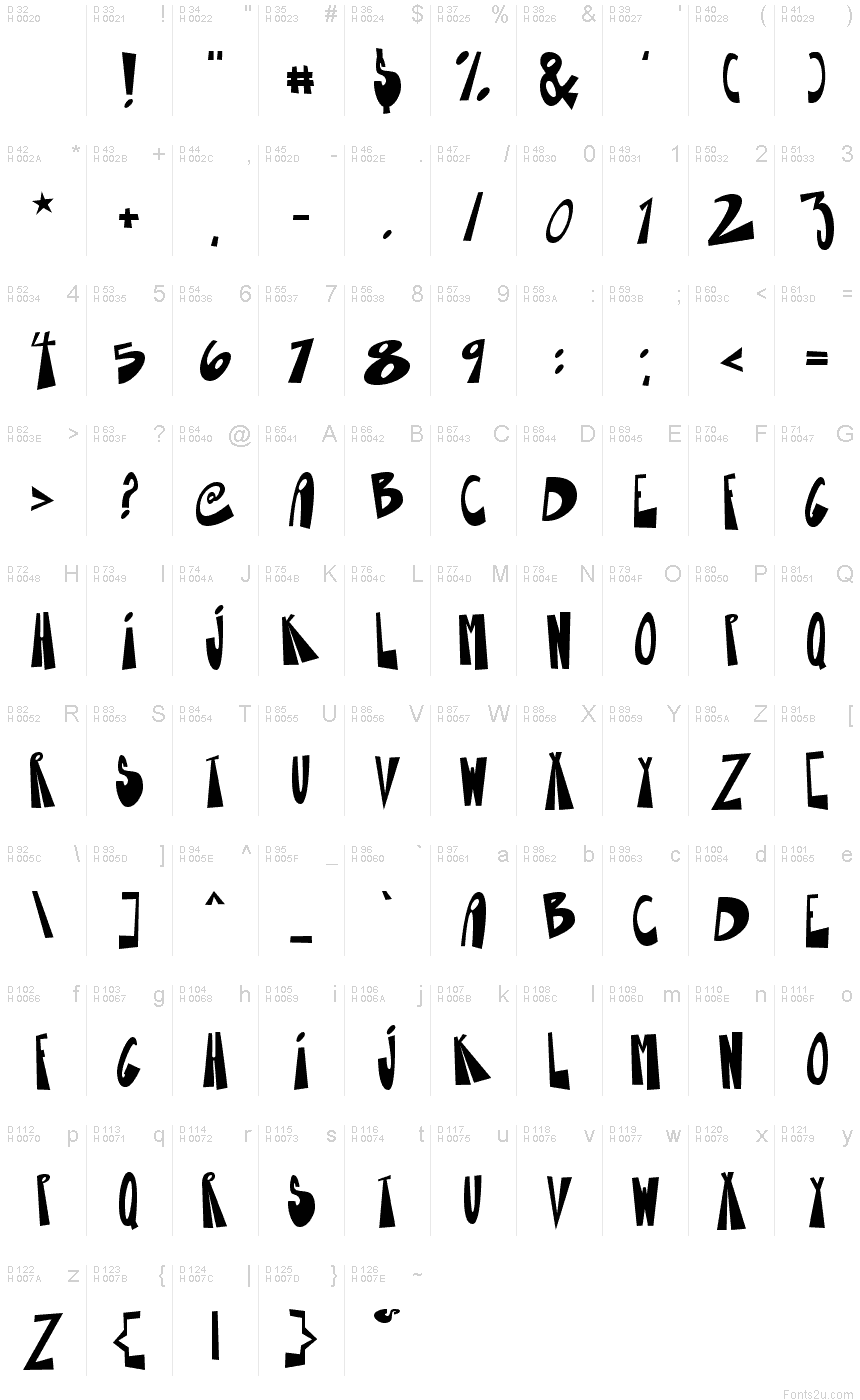
Gnarly von Jason Skoog ist eine kostenlose Comic-Display-Schriftart mit wilder, handgeschnittener Energie – wie direkt von einem Zine-Cover oder einem Skateboard-Deck. Die hohen, schiefen Buchstaben wirken, als wären sie eher geschnitzt als gezeichnet, was jedem Wort einen rauen DIY-Look verleiht. Ihr Rhythmus ist locker und lebendig, sodass selbst kurze Phrasen auf dem Bildschirm oder Papier sofort Aufmerksamkeit erregen.
Nutzen Sie Gnarly für Überschriften auf Konzertpostern, Skateboard-Grafiken, Surf-Brands, Comic-Titeln, YouTube-Thumbnails, Stickern oder Kinderbüchern, wenn es mal richtig laut sein soll. Diese kostenlose Schrift kommt groß am besten zur Geltung; kombinieren Sie sie am besten mit einer schlichten, neutralen serifenlosen Schrift im Fließtext, damit die markanten Buchstaben von Gnarly im Mittelpunkt stehen.